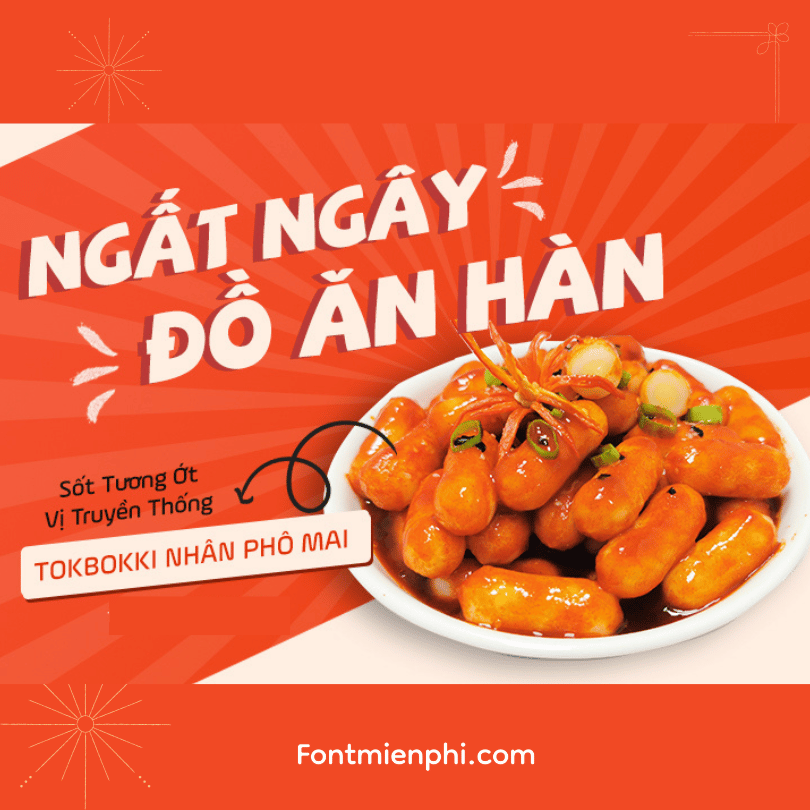
Combo font thiết kế ẩm thực 1 , Sẳn hiệu ứng trong file Ps
Combo font thiết kế ẩm thực 1 , Sẳn hiệu ứng trong file Ps – KÈM HIỆU ỨNG PS ĐỘC QUYỀN
Bộ sưu tập Font Ẩm Thực 1 đã được Việt hóa hoàn chỉnh, đi kèm file Photoshop chứa hiệu ứng layer style độc quyền, giúp bạn tạo ra các thiết kế ẩm thực chuyên nghiệp chỉ trong 1 click!
✔ 3 font chữ ẩm thực độc đáo (1FTV Ẩm Thực 1 + 2 font bổ trợ)
• Viền nét cọ tự nhiên
• Hiệu ứng bóng đổ 3D
• Texture màu vintage
✔ Hỗ trợ đầy đủ dấu tiếng Việt